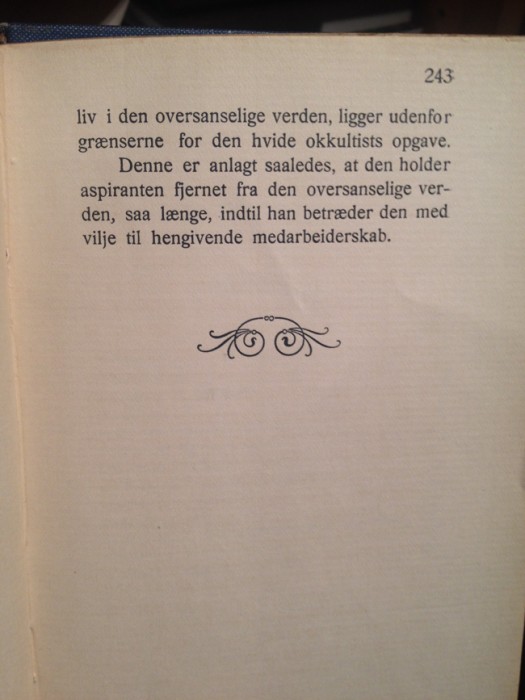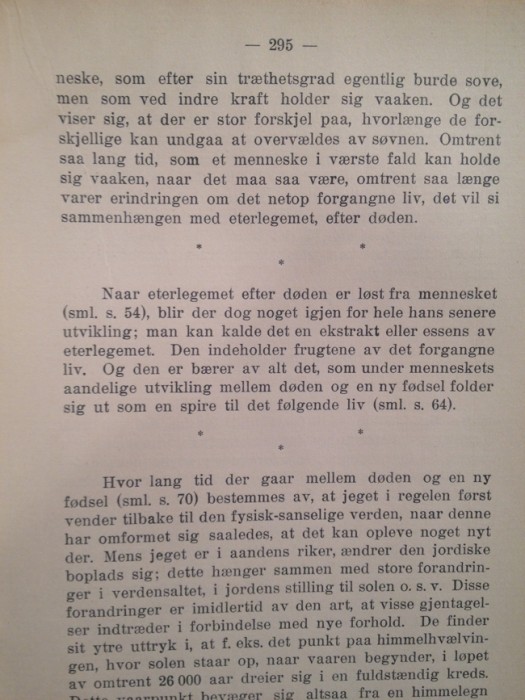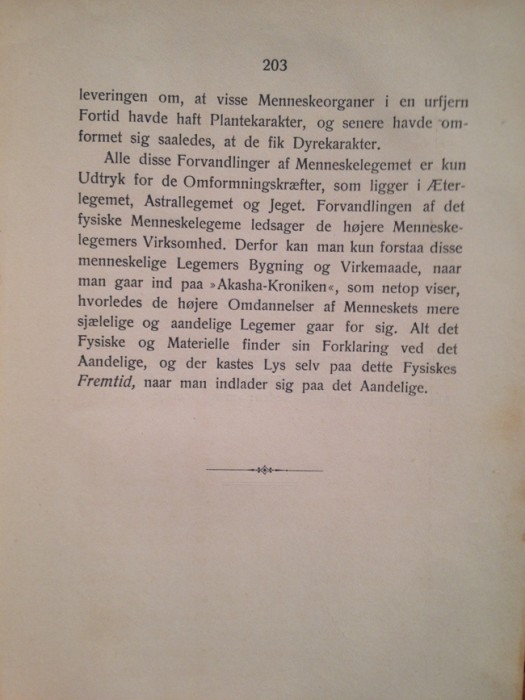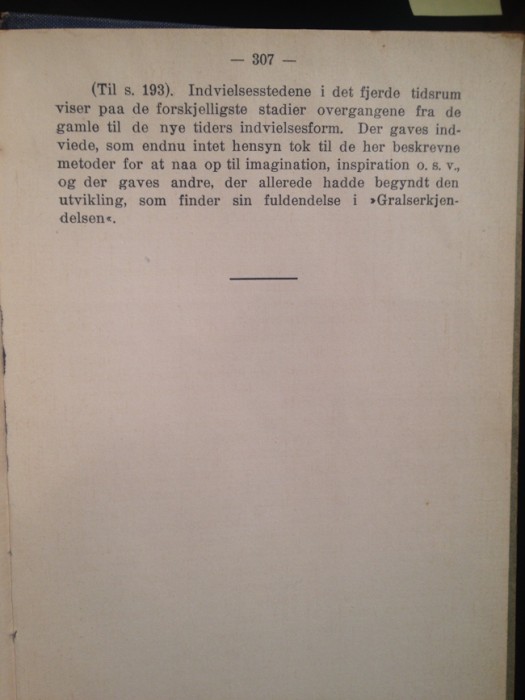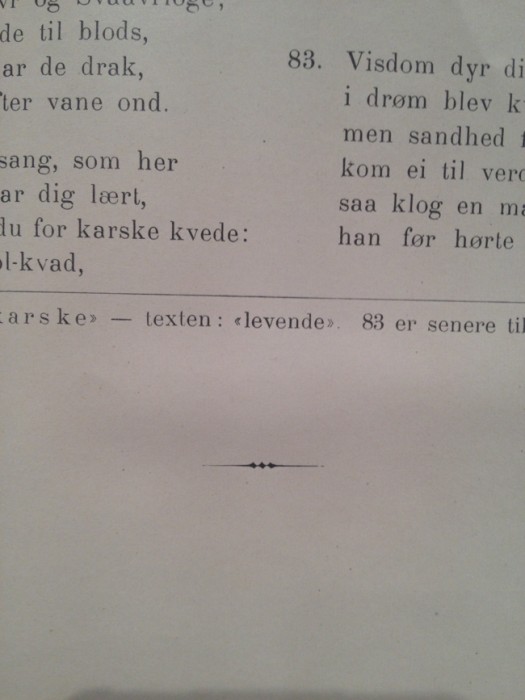
Zeichen, Kringel, Striche unter Absätzen
wißt ihr wie diese Zeichen hier heißen?
Sie werden nach Absätzen oder ganz am Ende, meistens in älteren Büchern, benutzt.
Es können Sterne, Striche, Kringel etc sein.
Die Zierlinien heißen im Bleisatz Zier- oder auch Schlusslinien, wenn sie nur von der Mitte her verjüngen werden sie auch englische Linien genannt. Die Sternchen sind Sternchen aus einer Schrift und das andere nennt man Zierrat oder Ornament oder (wenn es sich nach unten verjüngt) Schlussstück.
Das in dem ersten und dem letzten Bild wird Englische Linien genannt. Wenn es in der Mitte verdickt und zu den Enden hin dünn wird; ungeachtet einer möglichen (zusätzlichen) Ornamentierung. Im Englischen nannt man das ornamental rules.
Für die anderen Beispiele gibt es keine besonderen Begriffe.